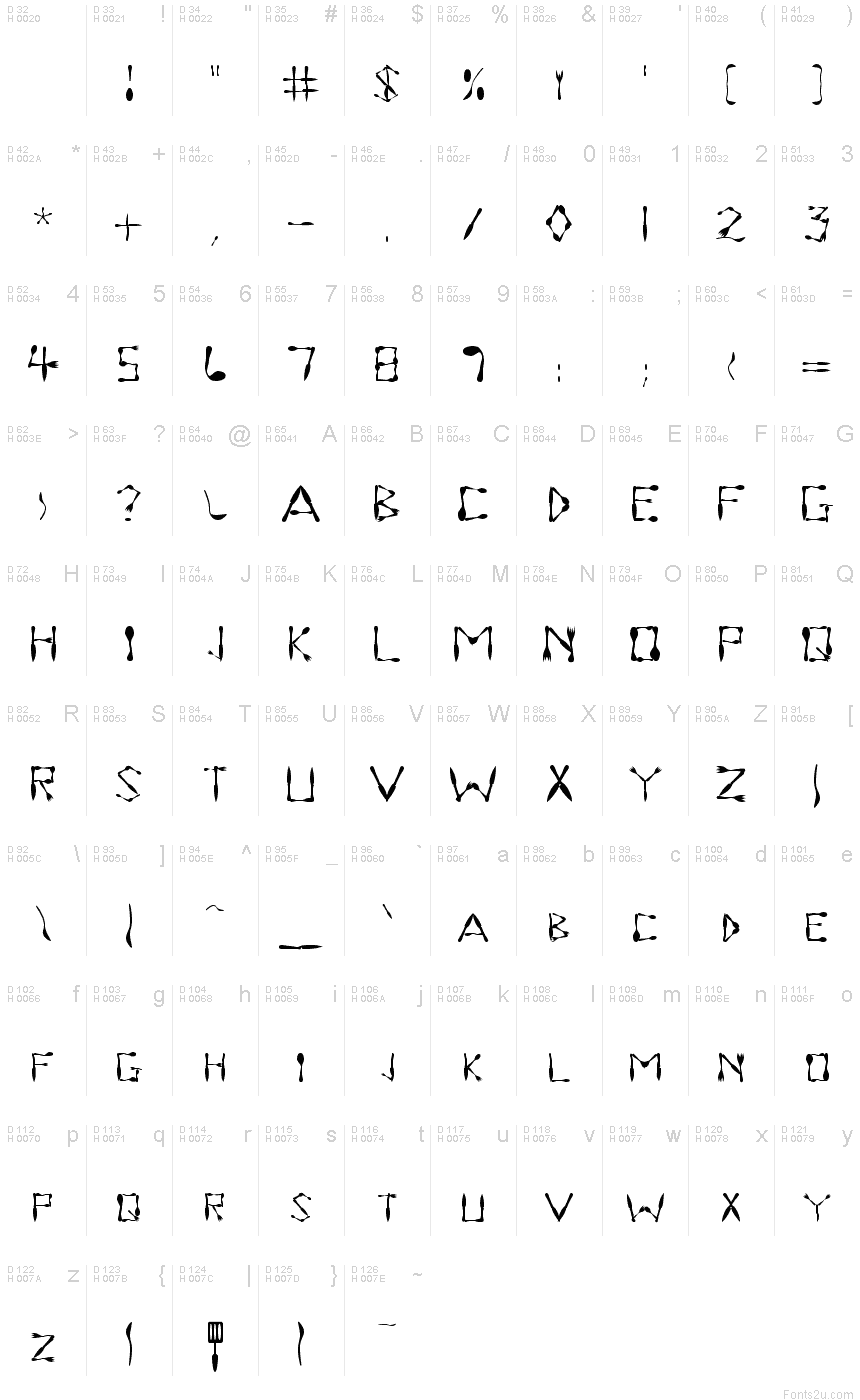
Dinner di Robert Schenk è un carattere display gratuito a tema posate, realizzato con le sagome di forchette, coltelli e cucchiai. Ciascuna lettera è assemblata come un pittogramma compatto anziché essere disegnata con tratti ordinari. Le forme sono nette e teatrali.
Le immagini di posateria possono diventare parte delle illustrazioni su menu di ristoranti, packaging alimentari e locandine di eventi. La grafica dei caratteri è particolarmente indicata per chef, servizi di catering e locali di ristorazione alla ricerca di un richiamo visivo giocoso legato alla tavola.